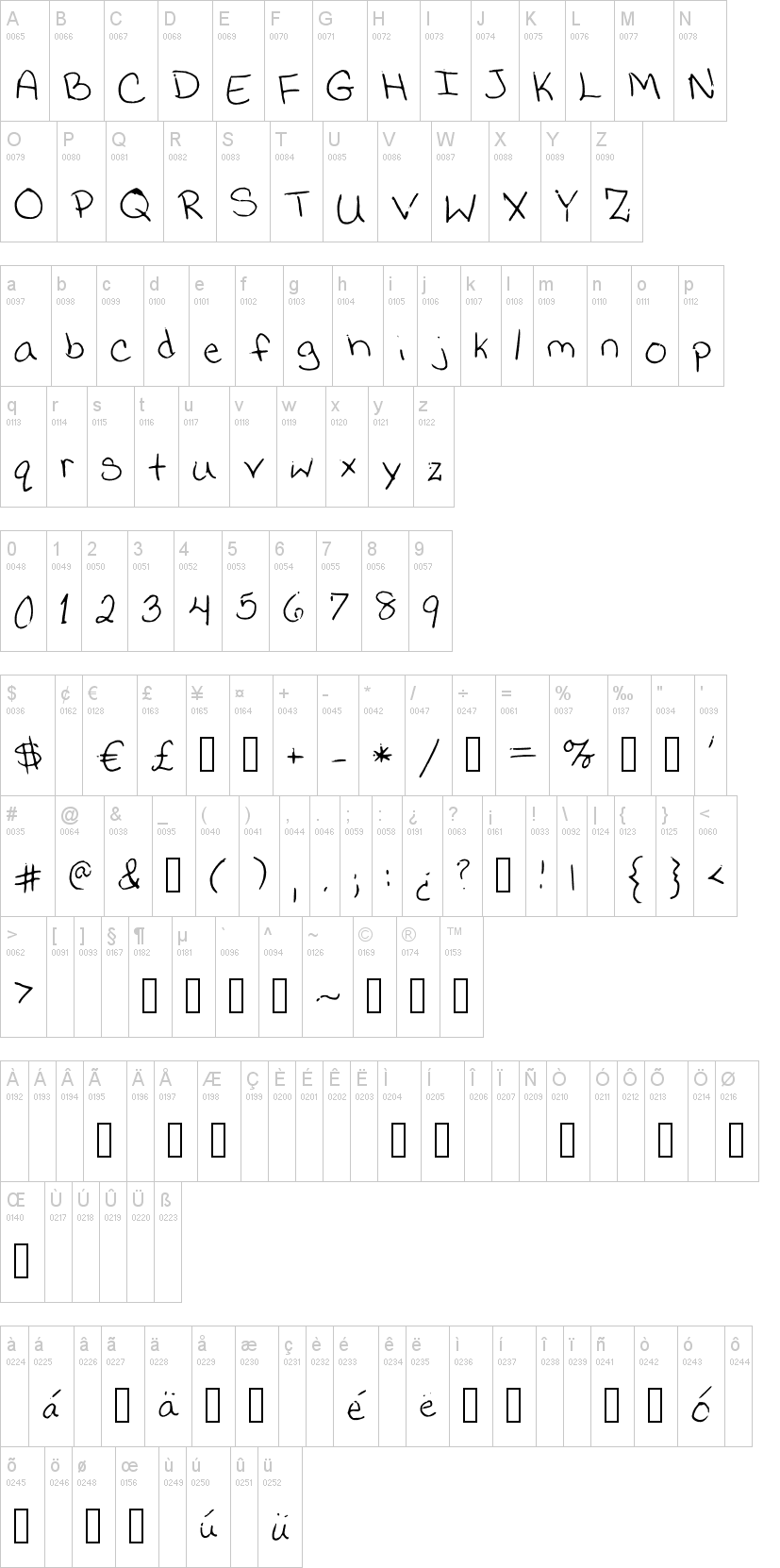
Jessica Print是一种现代、手写风格的字体,由设计师Ellen Luff于2015年创作。这种字体拥有圆润、流畅的线条和自然的笔画,使其看起来非常舒适和可阅读。 Jessica Print字体适用于许多设计领域,如品牌标识、海报、印刷品、包装设计、插图和手写样式的文本排版。该字体还包括了一些特殊字符和符号,使得设计人员可以在其设计作品中更加多样化和创新。内容介绍
Jessica Print是一款非常不错的手写艺术字体,具有很好的视觉感,适合于文化类的宣传设计、商业类品牌的广告和产品包装设计以及个性化文字排版等较多场景。